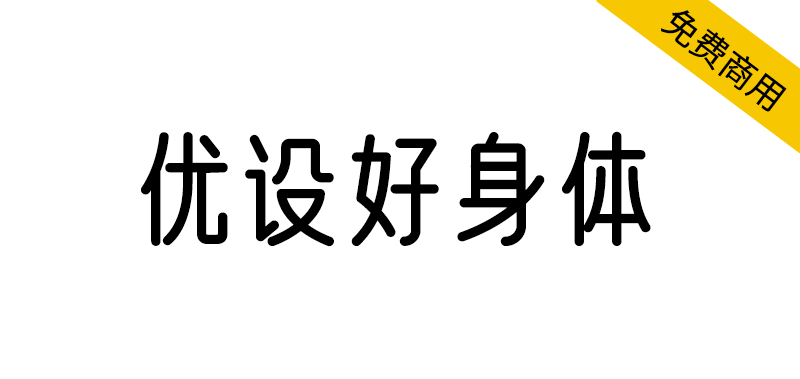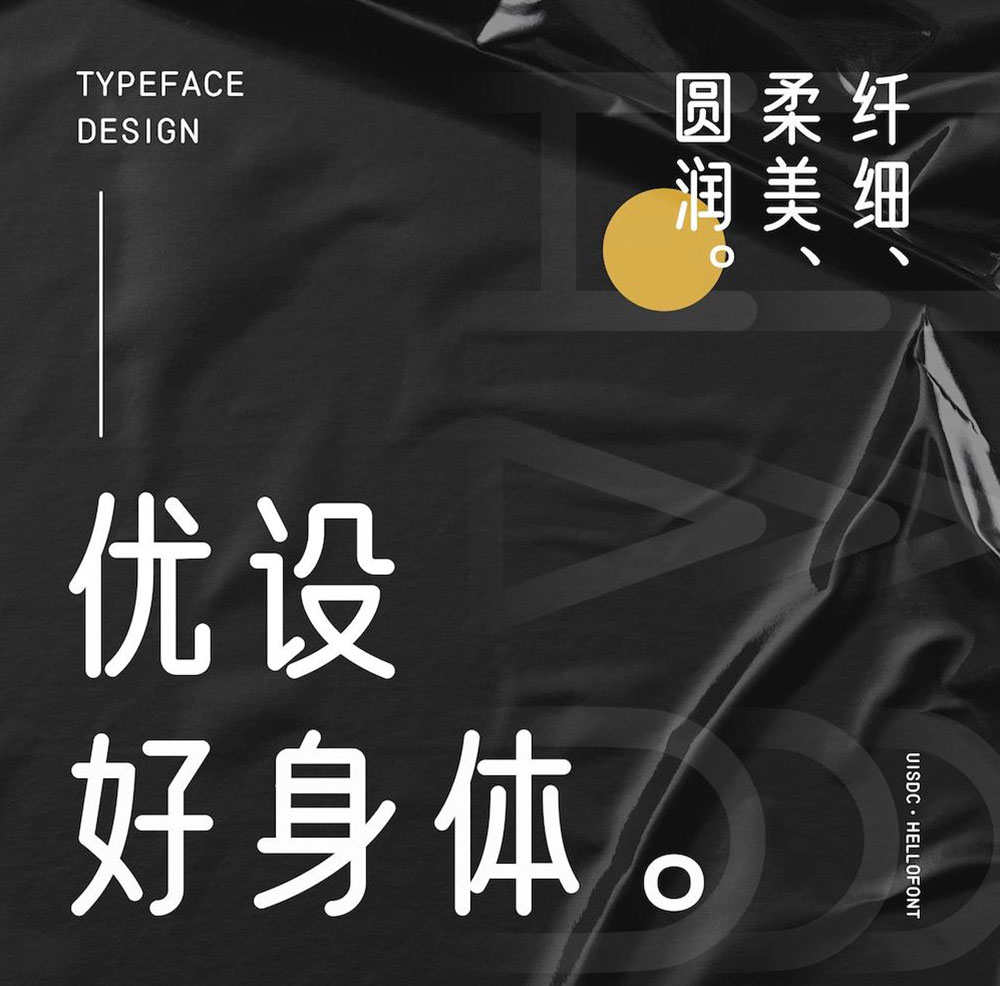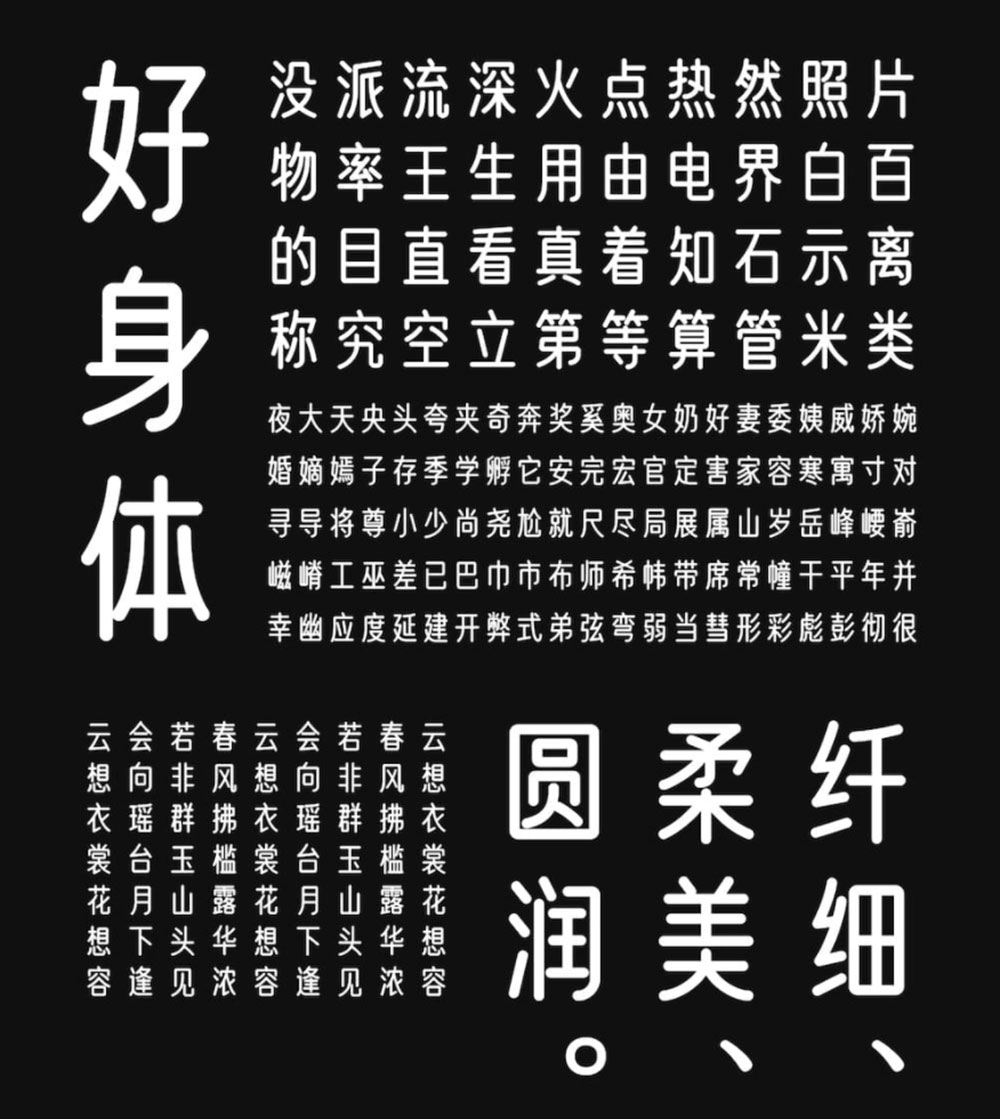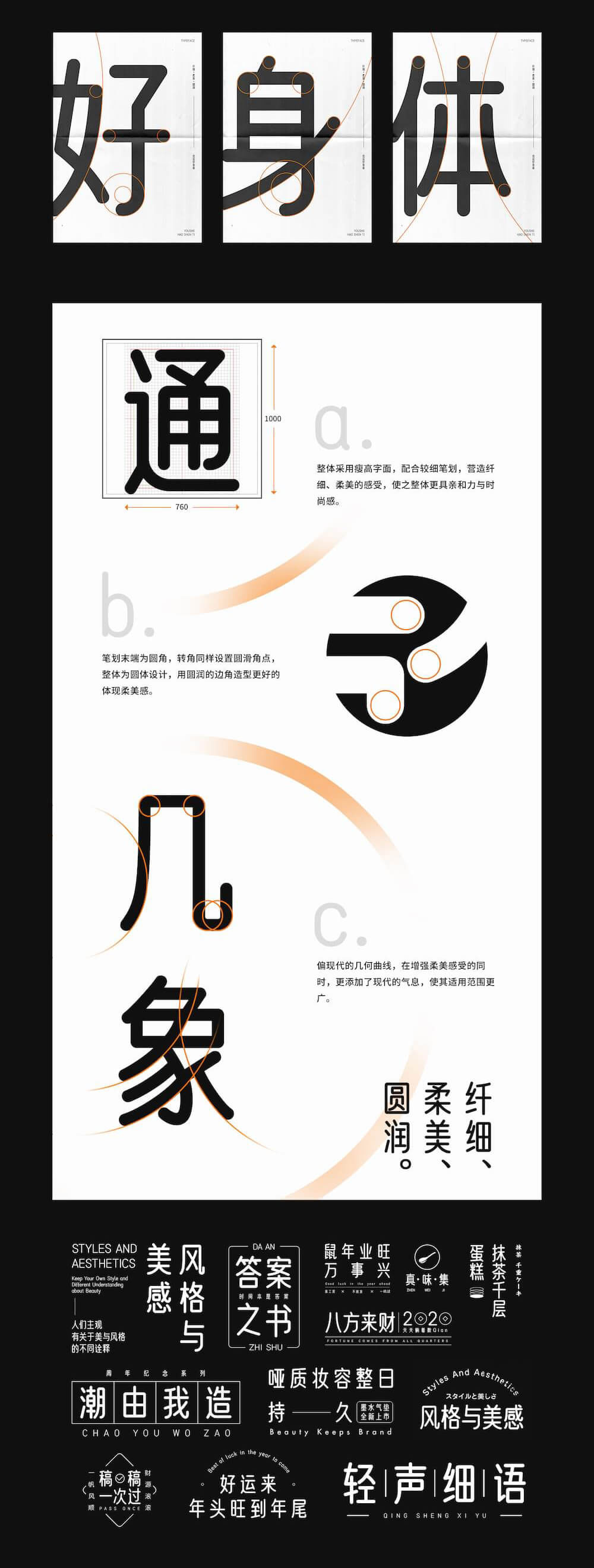
【优设好身体】圆柔纤细,有亲和力和现代感的字体
优设好身体是一款亲和力、现代感极强的专业美术标题字体。它以圆体字型为基础,通过瘦高的字面、偏向几何的曲线,让整宽字体富有亲和力和时尚感。在同样的面积里,更窄的字面就意味着能容纳更多的信息,所以这款字体非常适用在需要体现亲和力与时尚感的各类品牌宣传广告和产品包装设计的标题上。
优设好身体与「优设标题黑」沉稳有力兼具速度感的思路不同,「优设好身体」的整体气质偏向圆柔纤细,设计上更加富有亲和力和现代感,2套字体互为补充,可以覆盖绝大多数的设计场景。